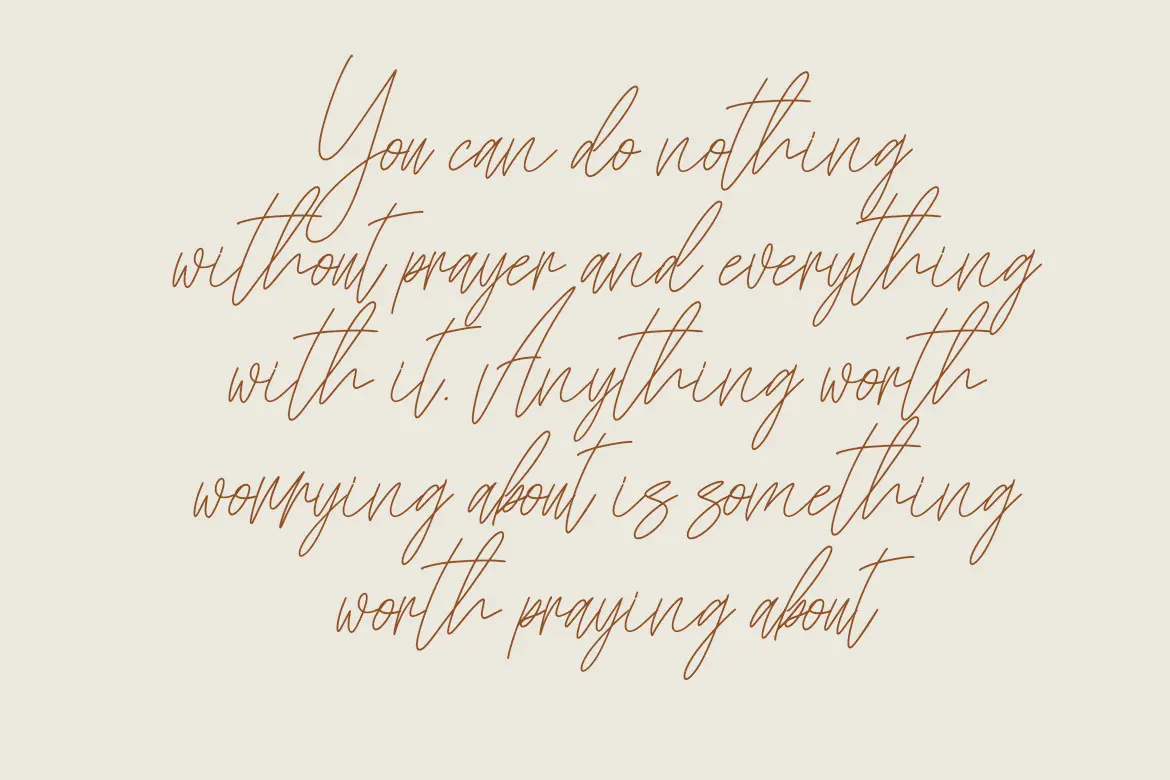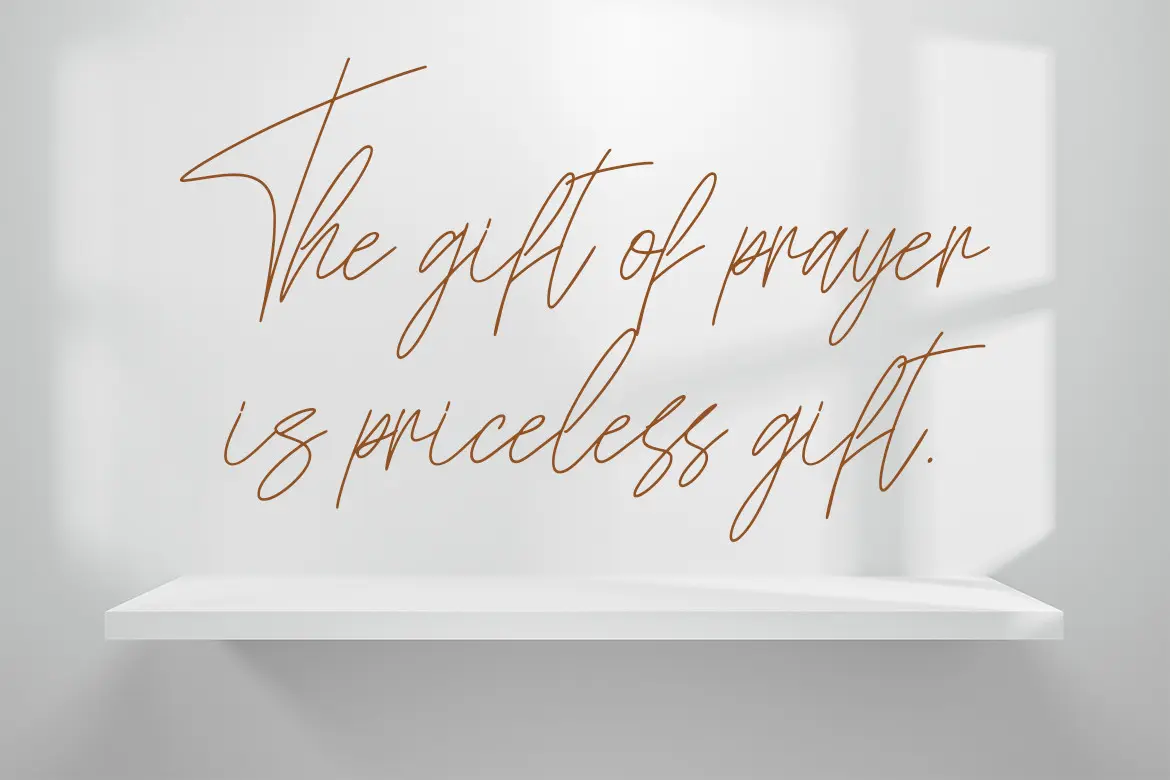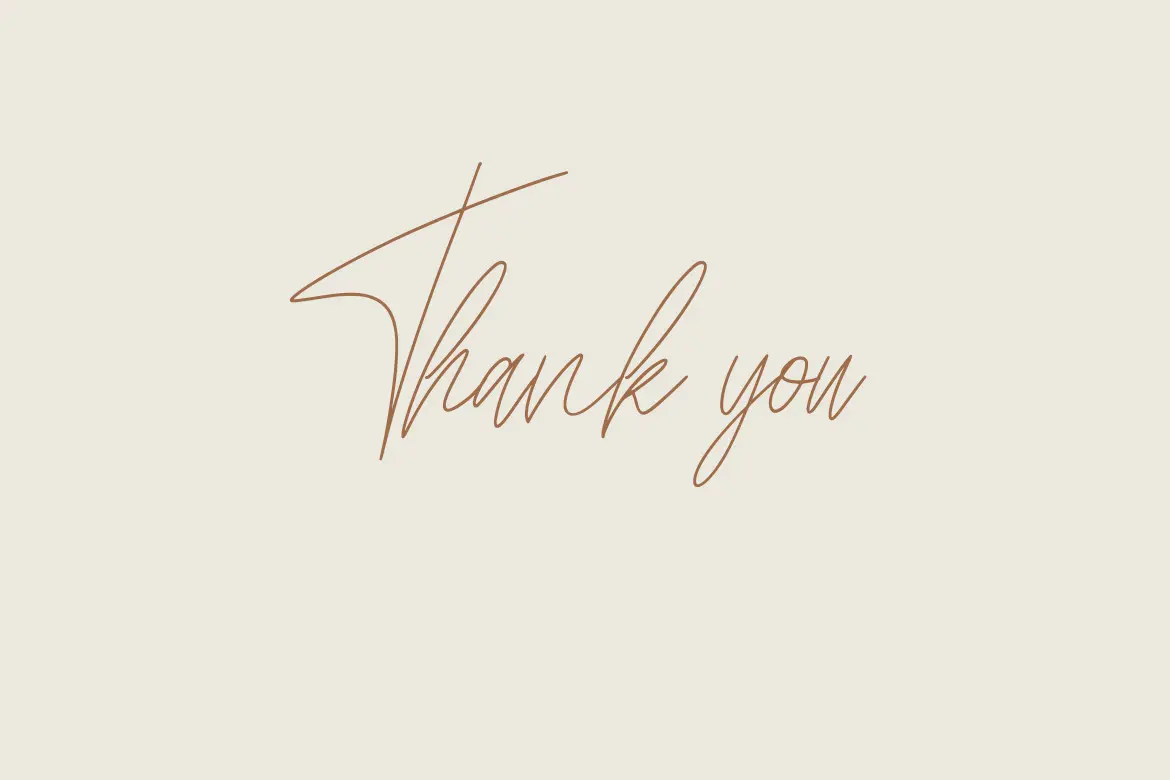
فونت امضا و سرهم
Kathilass یک فونت اسکریپت ظریف، نازک و بسیار چشمنواز است که با استایل الگانس، لطیف و دستنویس خود، جلوهای رمانتیک و هنری به طراحیهای شما میبخشد. این فونت برای پروژههایی که نیاز به حس زیبایی، ظرافت و جذابیت بصری دارند انتخابی فوقالعاده است.
⭐ ویژگیها
- سبک Script با حروف نازک و graceful
- مناسب برای طراحیهای:
- دعوتنامه عروسی
- استیشنری و کارتهای هنری
- پستهای شبکههای اجتماعی
- لوگوهای ظریف و برندینگ لوکس
- کاردستی و پروژههای خلاقانه
- استایل رمانتیک، چشمگیر و بسیار زیبا